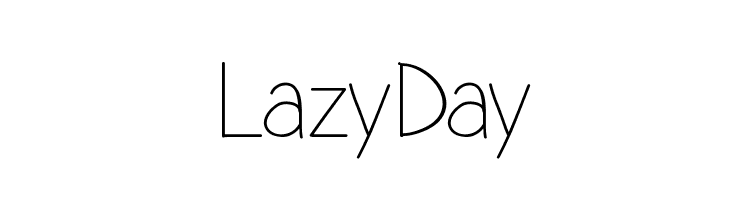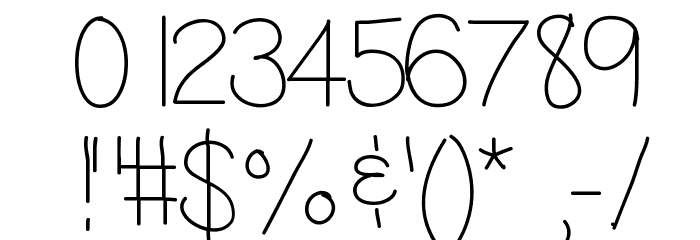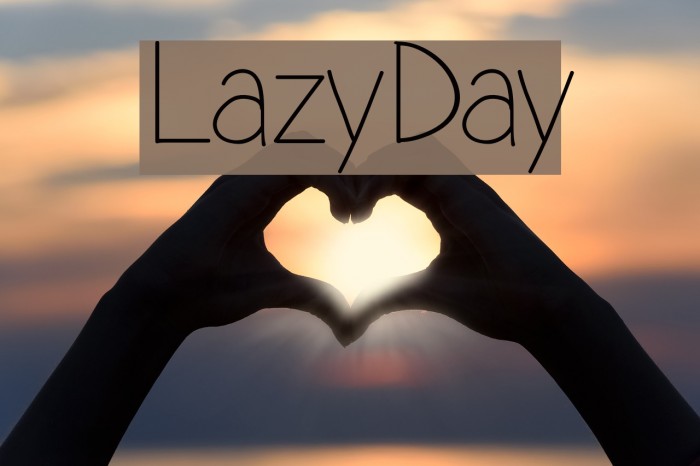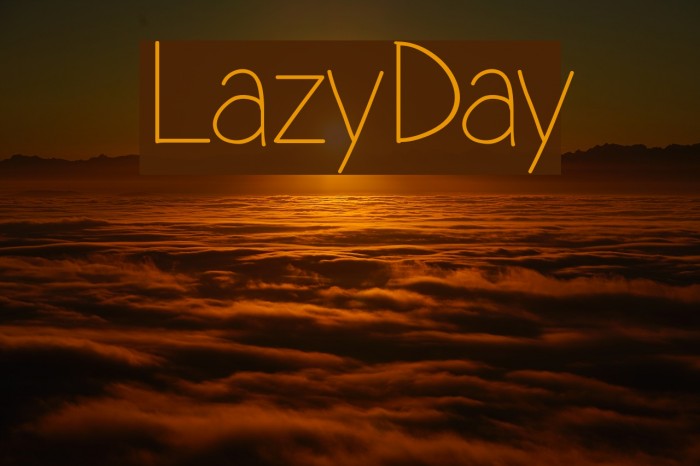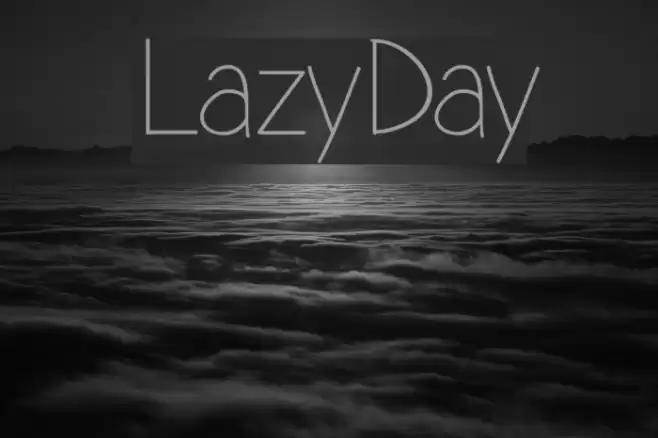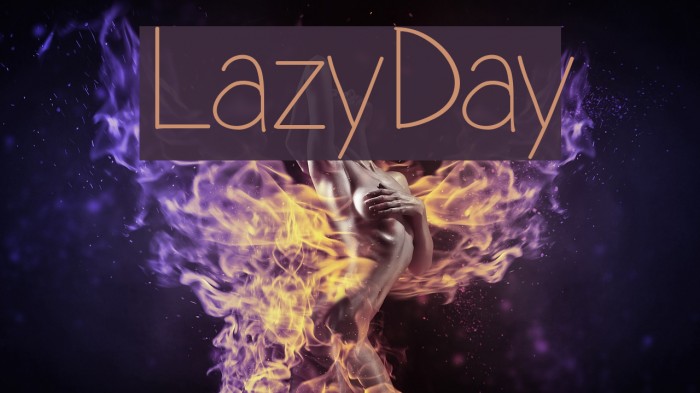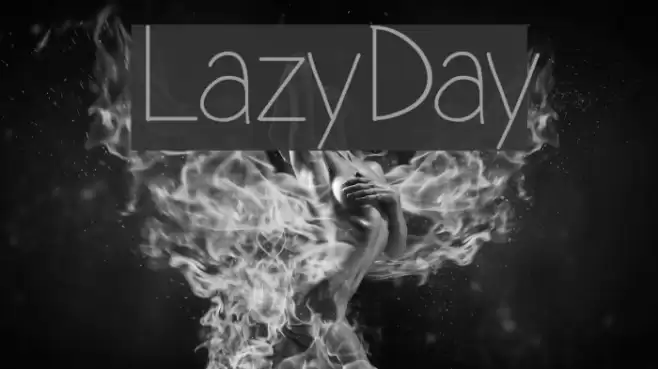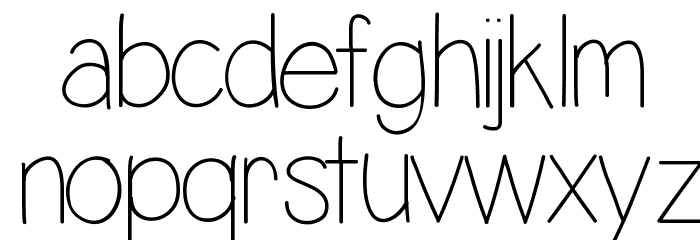
LazyDay Font
| Gesamtstil | Playful |
| Vorgeschlagene Projekte | Ideal for children's books, creative branding, casual invitations, and playful social media graphics. |